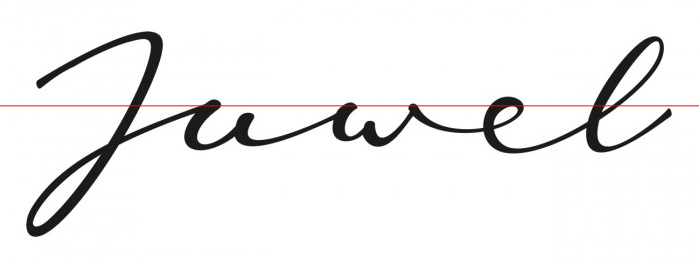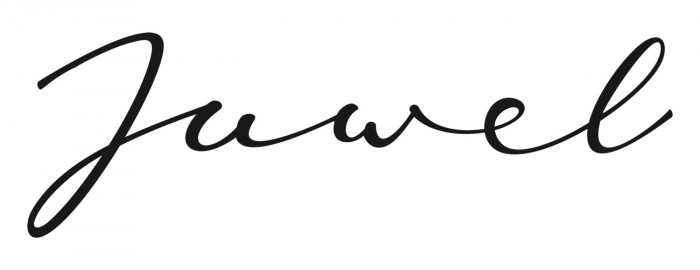
Unbekannte Handschriftart
Haben es auch schon mit WhatTheFont etc. versucht aber leider ohne Erfolg.
Ich glaube nicht, dass das einer Satzschrift entspringt. Die Anschlüsse der Buchstaben sind alle auf unterschiedlichen Höhen, das spricht einfach dagegen.
Die Anschlüsse sind aber alle gleich hoch, sonst gäbe es ja keine hübschen Verbindungen …